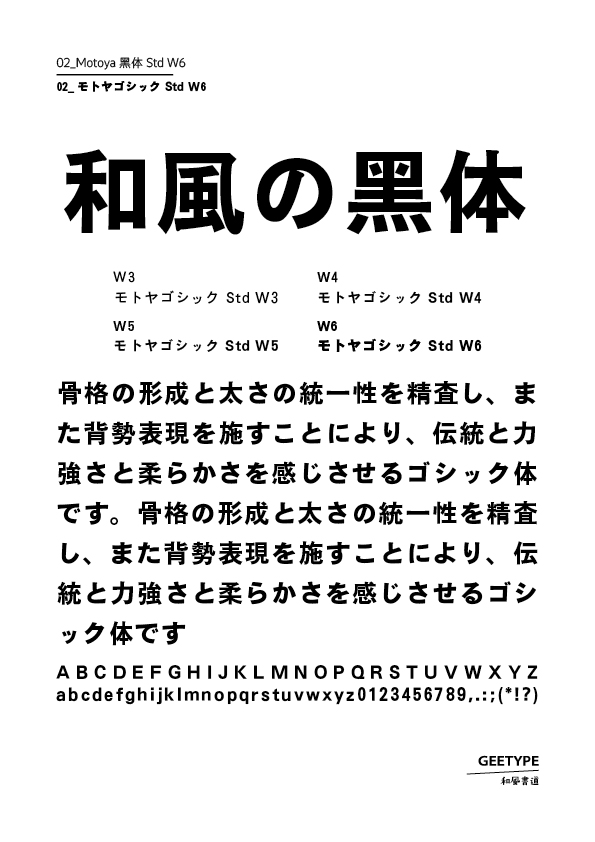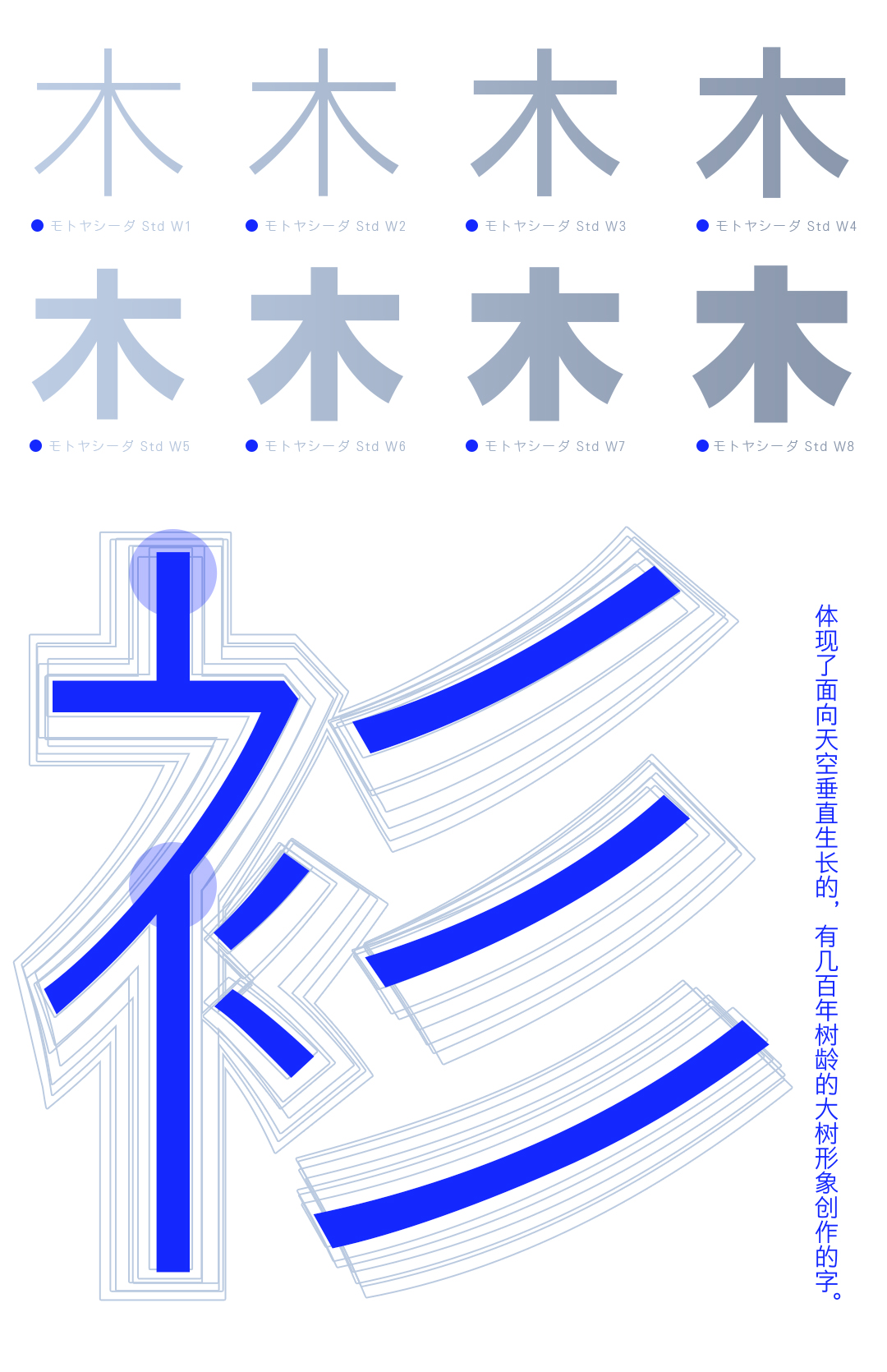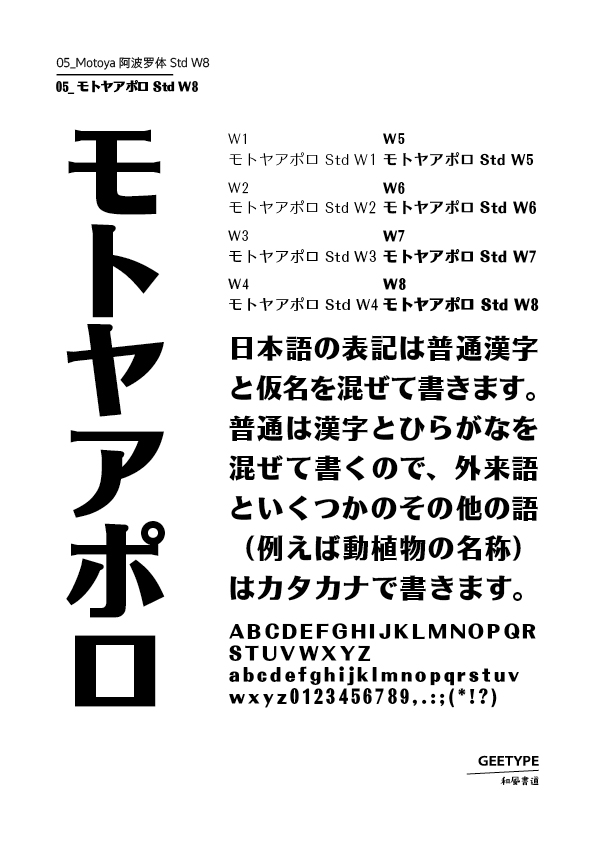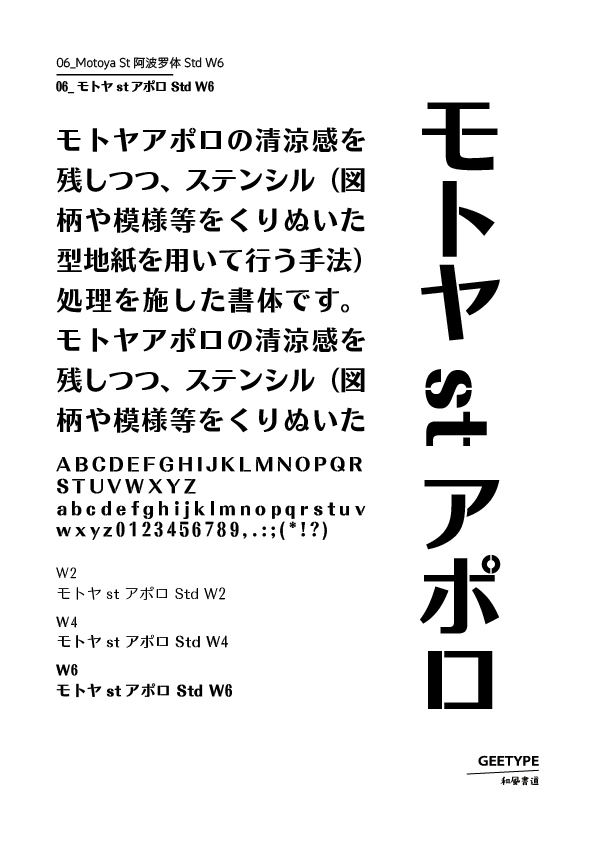
2021最经典的91款Motoya日本语字体,和风书道日本语出海字库正式上线发布
导语2021年,锐字潮牌字库、GEETYPE极字和风字库与拥有99年历史的日本专业字库公司MOTOYA达成战略合作,上线91款日本语字体!同时,开创和风书道日本语出海字库,旨在为中国企业、用户带来经典的日本语字体及出海解决方案。和风书道日本语字库和风书道是专业日本语字库品牌。“和风”即地道的“日本风”,追求自然、和谐统一,返璞归真的文字之美。为中国企业、用户提供专业购买授权,包括品牌,广告,游戏,视频,动漫等...
2021年,锐字潮牌字库、GEETYPE极字和风字库与拥有99年历史的日本专业字库公司MOTOYA达成战略合作,上线91款日本语字体!同时,开创和风书道日本语出海字库,旨在为中国企业、用户带来经典的日本语字体及出海解决方案。
Motoya日本语字体
Motoya日本语字体开发始于1950年代,一直持续到今天。在此期间,Motoya日本语字体通过支持多种字体设置方法(例如,铅字体,排版字体,排版表盘和数字字体)虽然改变了其产品形式。然而,在多年的字体发展历史中,一直没有改变的是对“良好可读性”和“字符美”的追求。
Motoya日本语字体认为的字体可读性是从“大小统一”“倾斜调整”“粗细统一”“文字美”“汉字假名和谐”五个总平衡中诞生的。在Motoya日本语字体中,除了这样的“可读性”和“阅读舒适性”之外,“极好的可读性”是最大的特点。
モトヤ書体の開発は、1950年代から始まり現在に至っています。この間モトヤ書体は、鉛活字、タイプ活字、写植用文字盤、デジタルフォント(ビットマップフォント・アウトラインフォント)と様々な組版手段に対応し、その製品形態を変えてきました。しかし永年にわたる書体開発の歴史の中で、変わらないものが、「可読性の良さ」と「文字の美しさ」の追求です
91款MOTOYA
日本書体一览
モトヤ明朝(Motoya明朝体)
Std W2/ W3/W4/W5/ W6
motoya明朝(宋体)不论竖着排列或横着排列,都很容易读懂,因为文字的造型是在“日本书道”基础上制作的,所以“文字之美”尤为突出。正文文字用为了防止文字的布白平衡垮掉,将字体平衡更好扩展,设计成有流畅印象的字体。标题用的,则是使竖线下面鼓起,表现楷书柔软风格的字体。
モトヤゴシック(Motoya黑体)
Std W3/ W4/ W5/ W6
黑体字体,没有像宋体那样装饰横线和竖线的衬线和装饰线,骨骼线本身就是文字生命的字体。另外,横线也需要根据笔画的粗细进行调整,所以要使其具有线条粗细的统一性可以说是非常困难的字体。motoya的黑体字体系列,在克服这两个命题的同时,通过实施背势表现(竖线和横线两端的喇叭状表现),成为同时让人感受到传统、强力和柔和的字体。
モトヤシーダ(Motoya杉体)
Std W3/ W4/ W5/ W6/ W7/ W8
Cedar是指“杉”。是体现了面向天空垂直生长的,有几百年树龄的大树形象创作的字。Cedar的字制作时最大限度的伸展放大,取消了背势表现(竖线和横线两端的喇叭状表现),是呈现出简练的现代风格的字体,Cedar系列出众的可辨识性,不仅在印刷物上,在电视字幕、游戏、Web内容上也被频繁使用。
モトヤマルベリ(Motoya桑体)
Std W2/ W3/ W4/ W5/ W6/ W7/ W8
Mulberry是继承了Cedar的特征,可以说是Cedar的圆角版黑体字体。因为字体感的印象,用了同样是的树木的Mulberry“桑”这个名字。在开发Mulberry的时候,为了进一步扩大中部空间,让假名更圆润,让其看起来更像个圆角版黑体字体而进行了处理。最后的结果,Mulberry在充分的圆润的同时,还完成了同时具有Cedar的特征的流畅印象的字体。
モトヤアポロ(Motoya阿波罗体)
Std W1 / W2/ W3/ W4/ W5/ W6/ W7/ W8
阿波罗(Aporo)是将宋体的骨架(带有纵线的右边上的三角形的装饰)和装饰性骨架(带有纵线的右边和纵棒上端直角交汇部分征收的三角形的装饰)去除,中部较宽的字体。在数字化的过程中,使中部更宽,改变了斜线撇捺的形状。这是为了更加突出阿波罗的特征而重新设计的,更加强调了其清爽且摩登的形象。
モトヤstアポロ(Motoya St 阿波罗体)
Std W2/ W4/ W6
St阿波罗(StAporo),保留了阿波罗的清凉感,是为了用于版画和染色,工业用简易印刷等模板(条纹和图案等由型纸使用方法)进行印刷的技法,特意设计的,新风潮的字体。由于模板部分起到了点缀的作用,阿波罗给人的尖锐、优雅的印象更加突出。
モトヤ丸アポロ(Motoya阿波罗丸体)
Std W4/ W6/ W8
丸阿波罗(丸,即圆角)是以流畅明亮的形象为特征,从阿波罗衍生出的字体。通过将斜线的折角用圆弧来表现出柔和效果,点的位置和向右撇的笔画部分等不做成圆角保持锐角,在其中也散发出尖锐感。从正文中选出可用于标题的粗细,可以进行更加丰富多彩的文章排版表现。
Motoya日本语字体